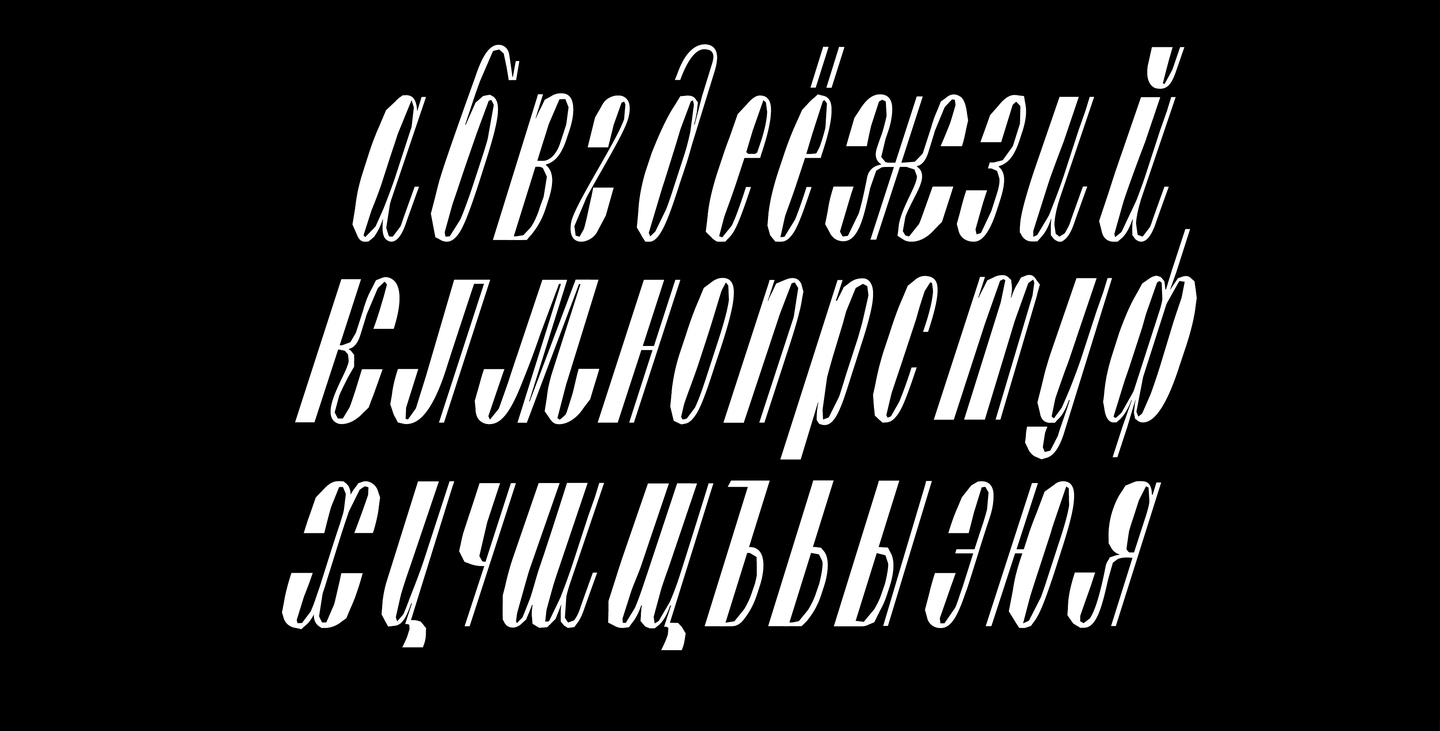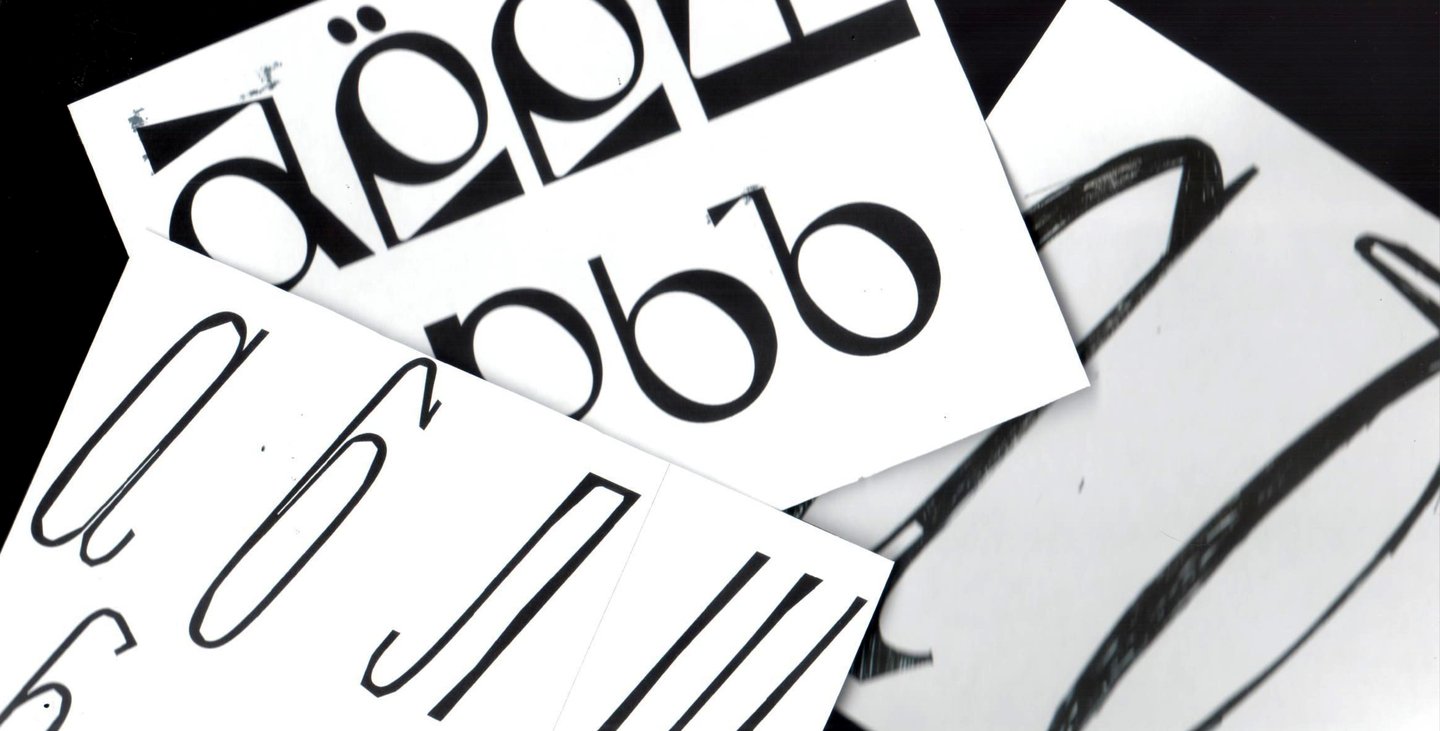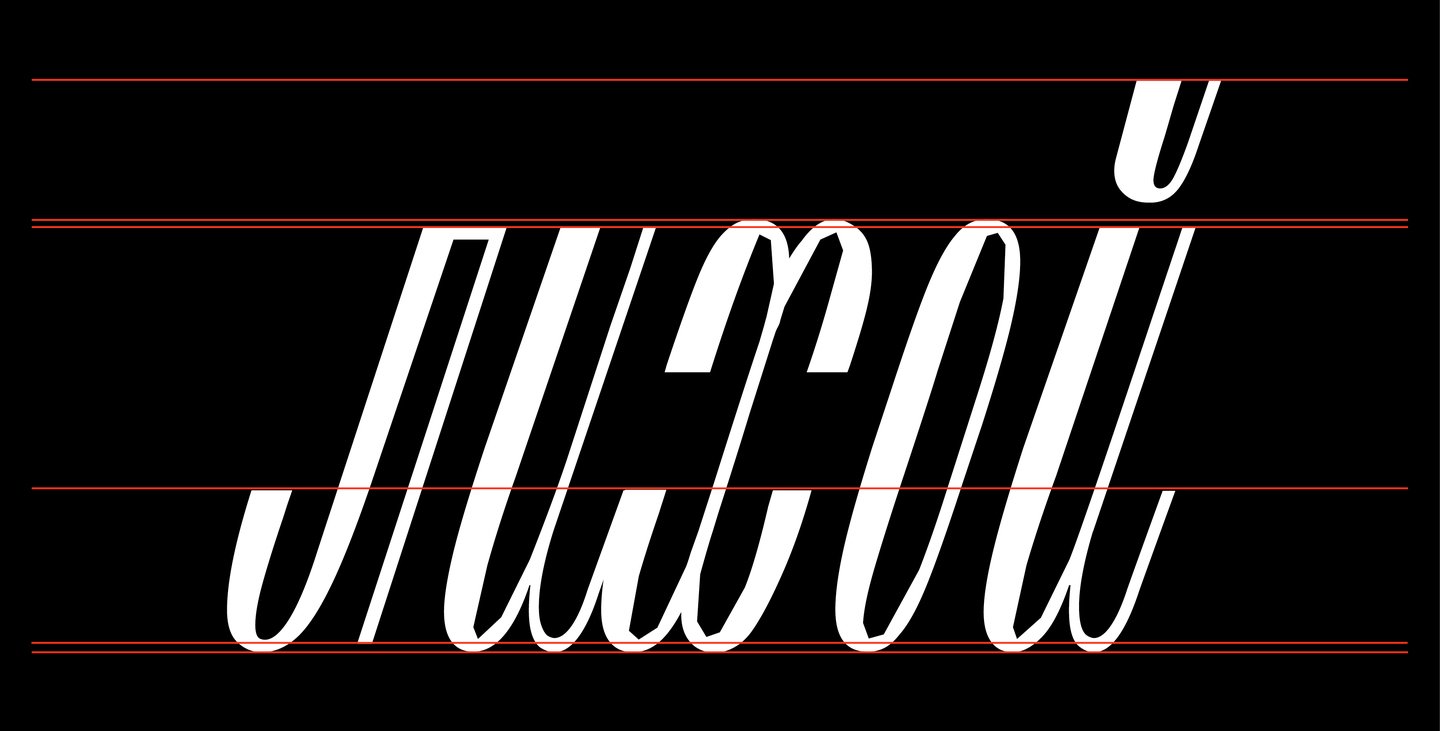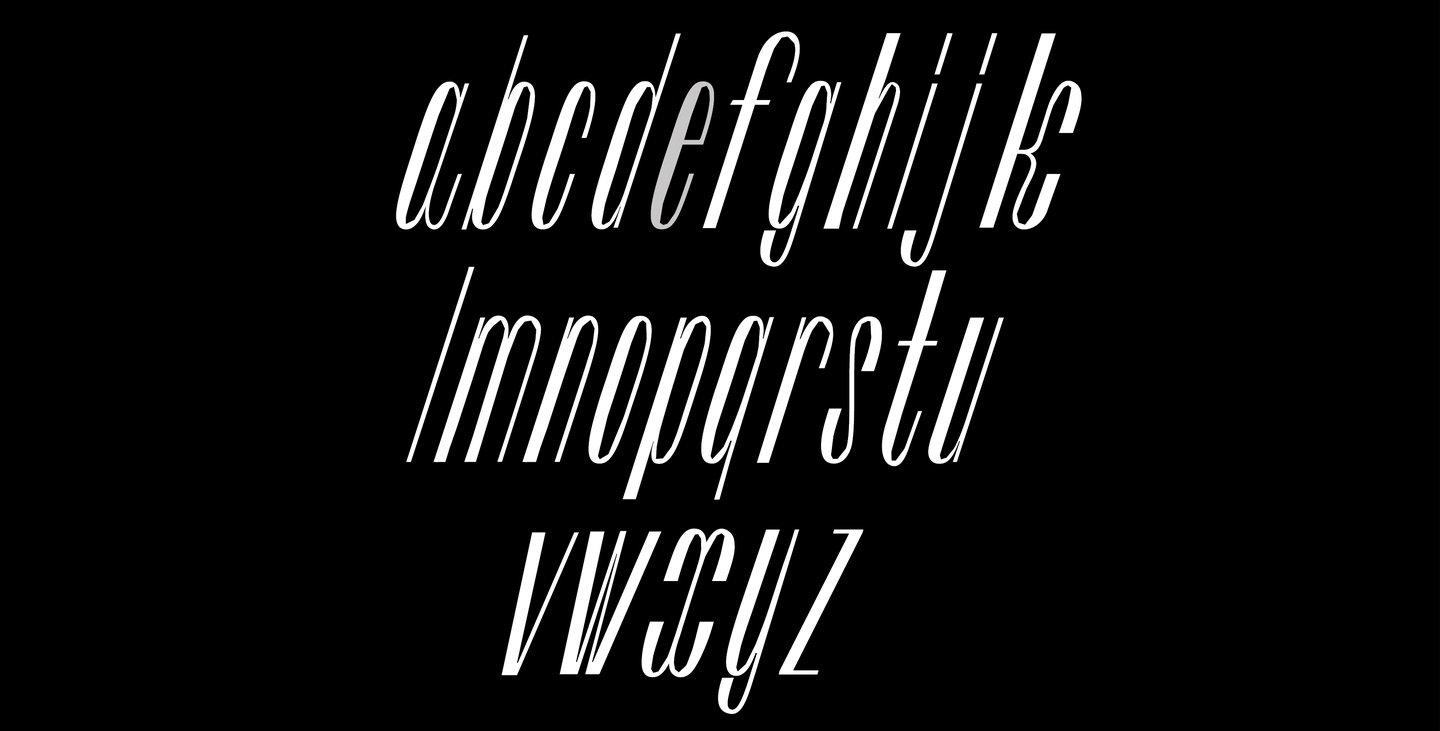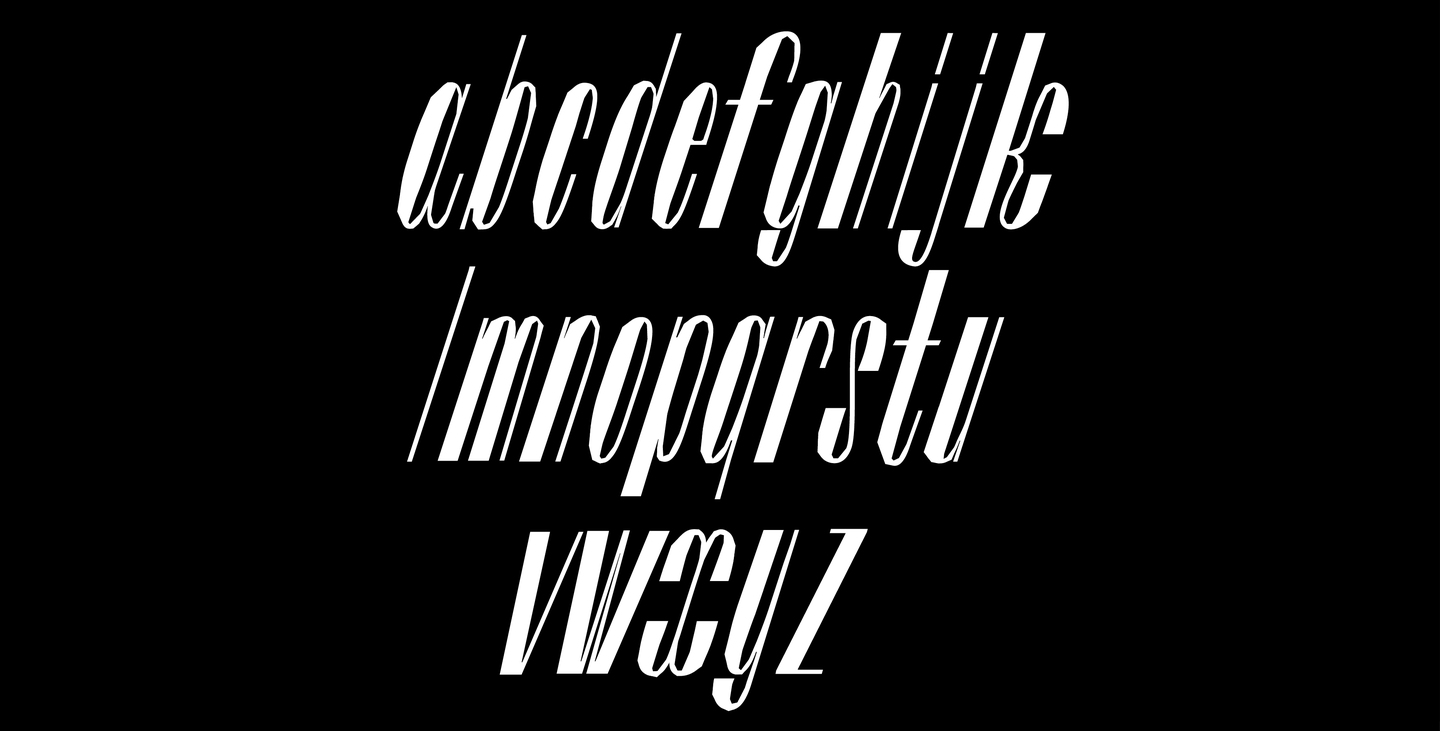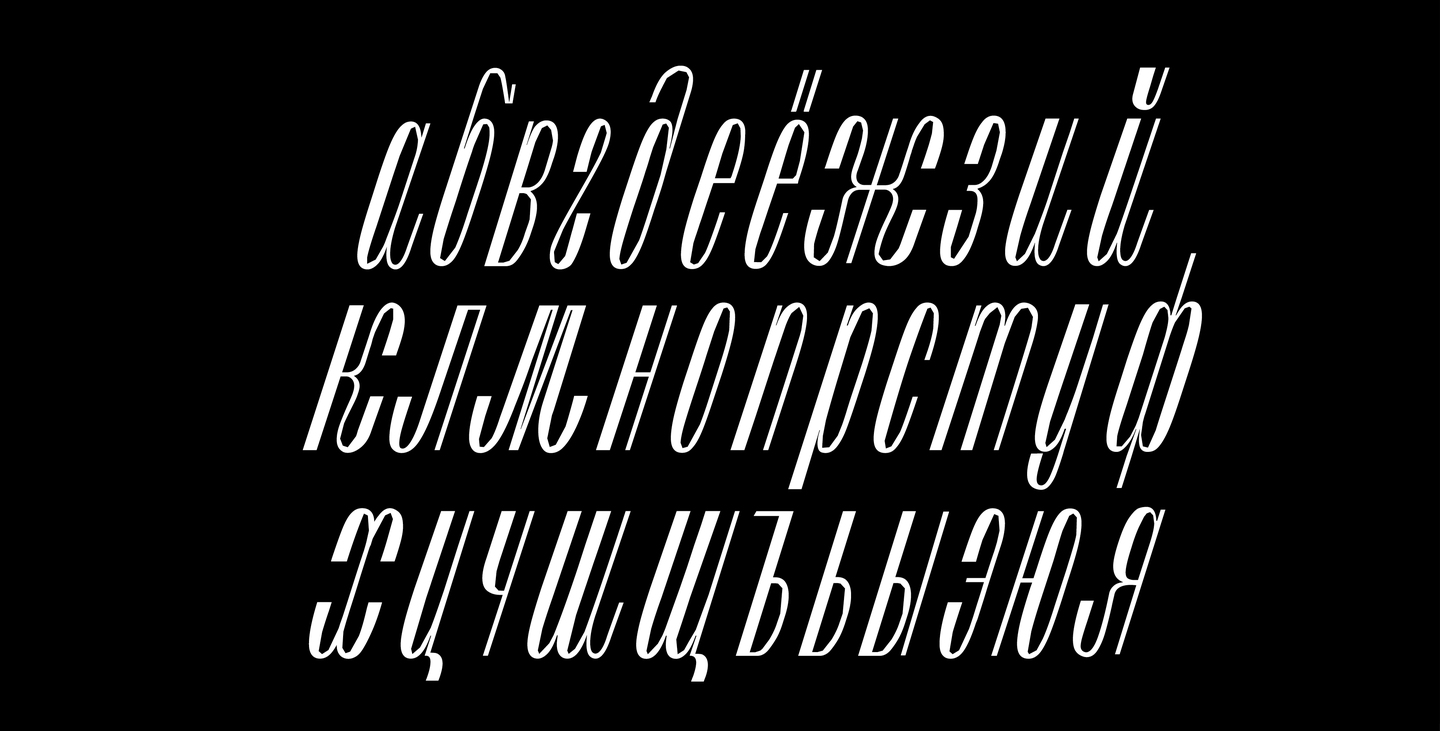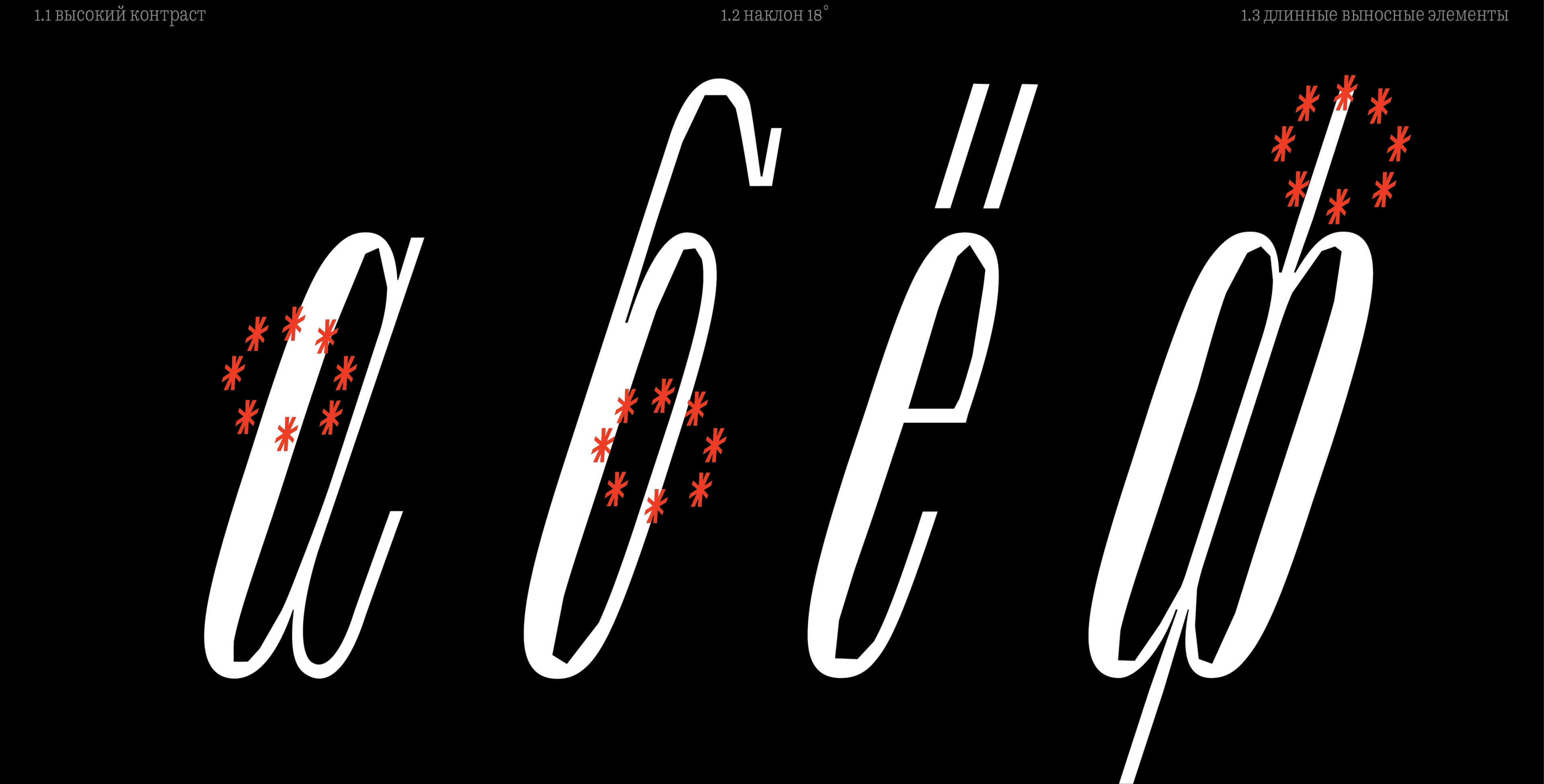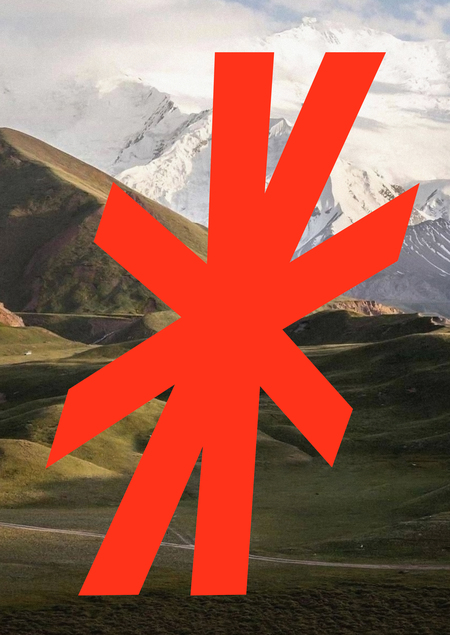
шрифт ЛИХО
Лихо — акцидентный шрифт, вдохновлённый природой Якутии: в его основе — мощные горные силуэты, плавная динамика рек и отголоски истории края. Контраст, выразительность и характер северной стихии объединены в единой пластике